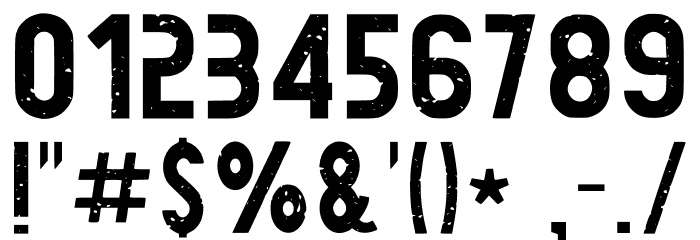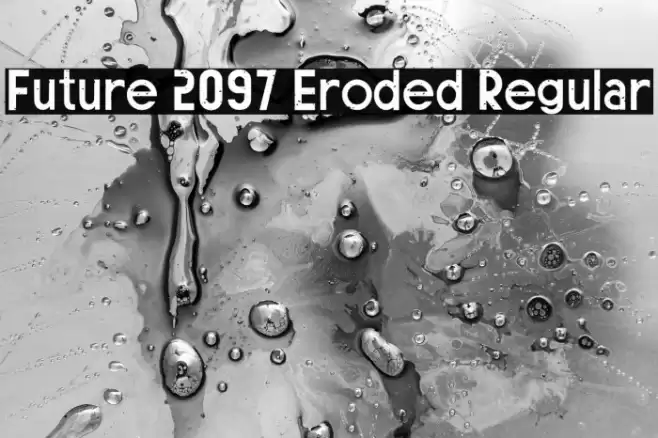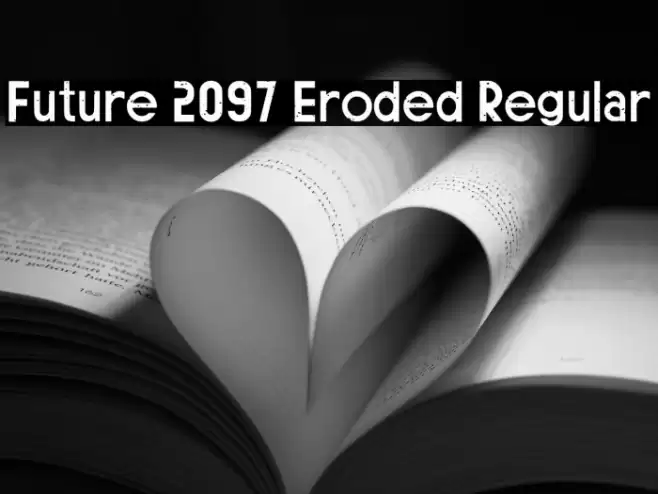
Future 2097 Eroded Regular Font
✎ Distorted Eroded
| Gesamtstil | Futuristic, Industrial |
| Vorgeschlagene Projekte | Ideal for sci-fi themed posters, video game titles, industrial design projects, and edgy branding materials. |